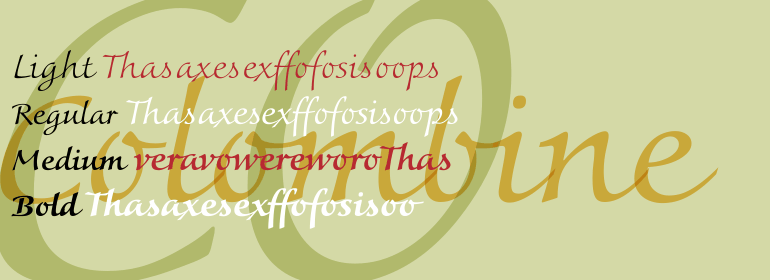
Colombine®
Colombine®,这款字体结构工整、笔画清晰,兼顾美观与易读性,适用于标题、正文、海报、包装、LOGO 等多种场景。字形优雅稳定,风格百搭耐看,适配日常排版与创意设计,让文字呈现更舒适、更具质感。Colombine®一笔一画,皆是细节,以均衡的比例、流畅的线条打造舒适视觉体验,字形端正大气,风格简约现代。无论是商业设计、品牌宣传还是日常排版,都能轻松驾驭,让文字更有格调与力量。Colombine®字体下载。
字体品牌: Linotype(Monotype) 设计师:Zapf-von Hesse,Gudrun 字体分类: 字体属性:外文 字符集:Unicode 发布时间: 2018